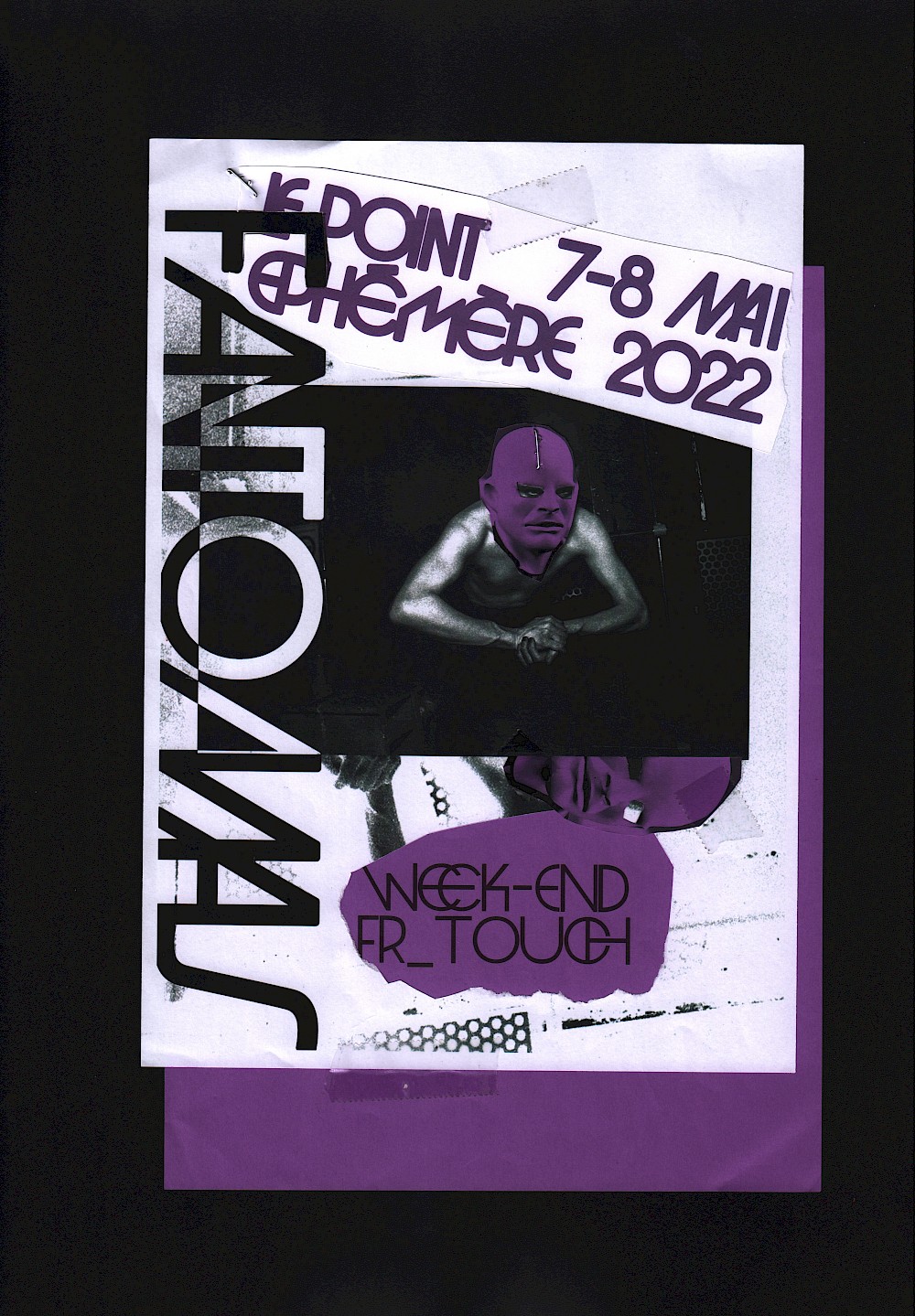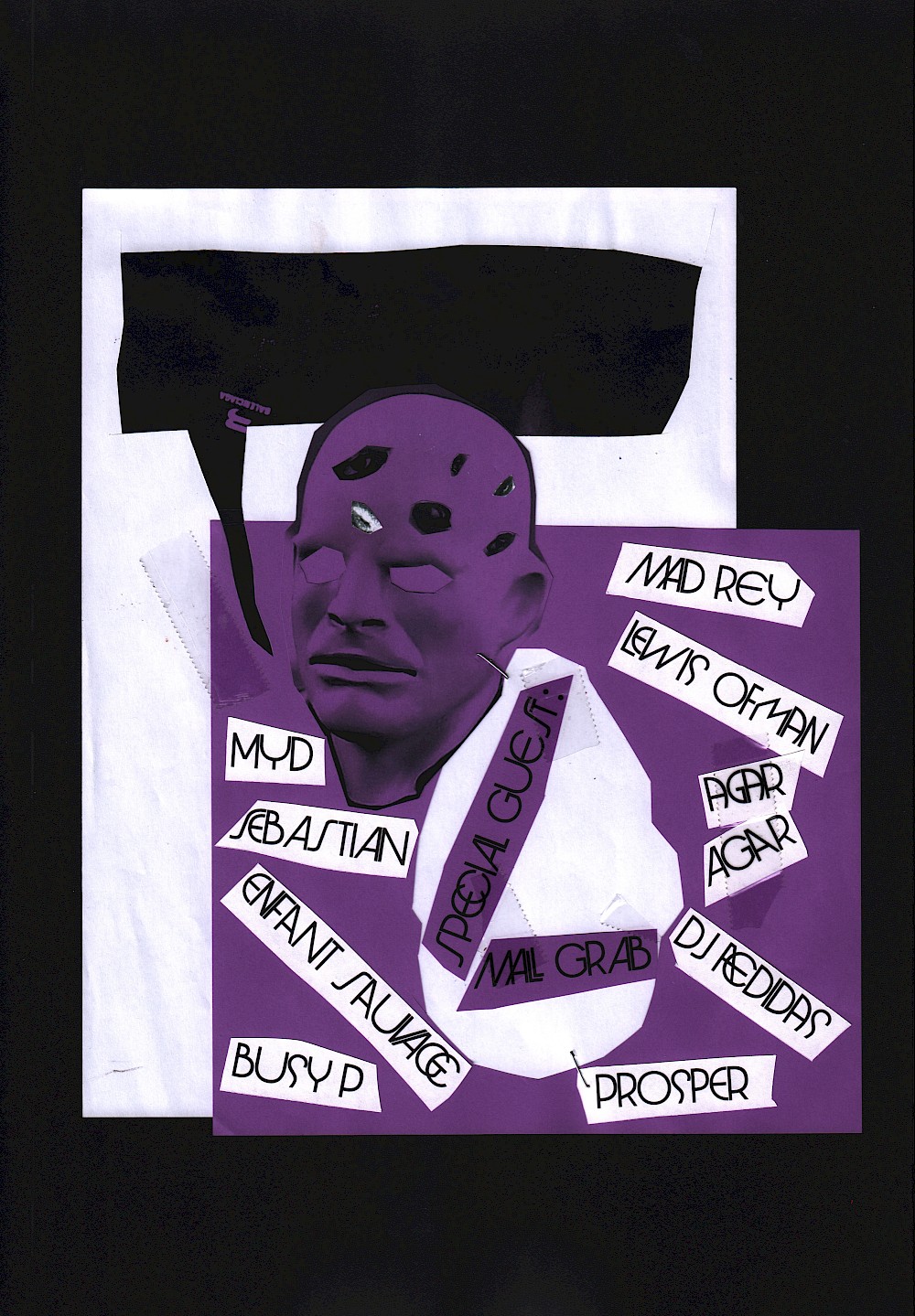
Je saurais pas expliquer l'origine du nom de la typo, mais au vu de l'affiche j'avais, à l'époque, une fixette sur le personnage de Fantomas…
Ahhh le DNMADe… Doux souvenir des cours de typo qui m'ont fait comprendre que faire des fonts était beaucoup plus dur que ce que je pensais. Pour commencer cette typo, notre prof nous donnait une photo de devanture de magasins avec quelques lettres. J'ai passé des mois à faire le reste des lettres en me pensant 100% original, avant de me rendre compte que c'était une copie wish de l'ITC Avant-Garde (ಠ ⌓ ಠ)
Fantomas